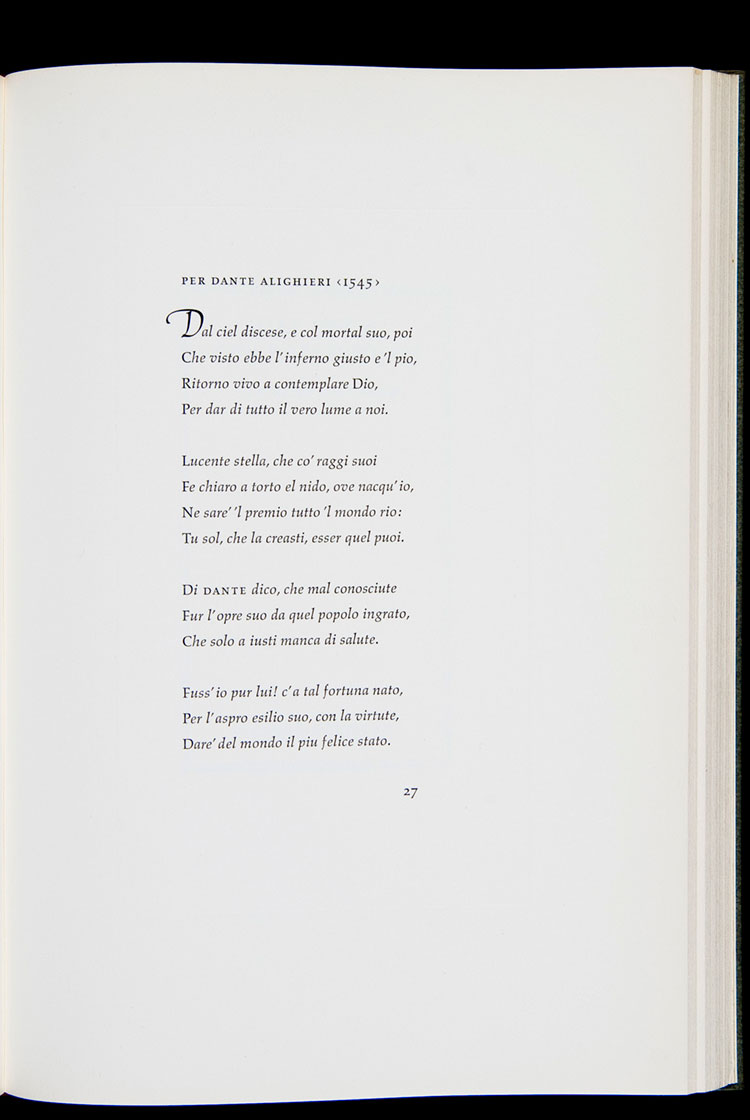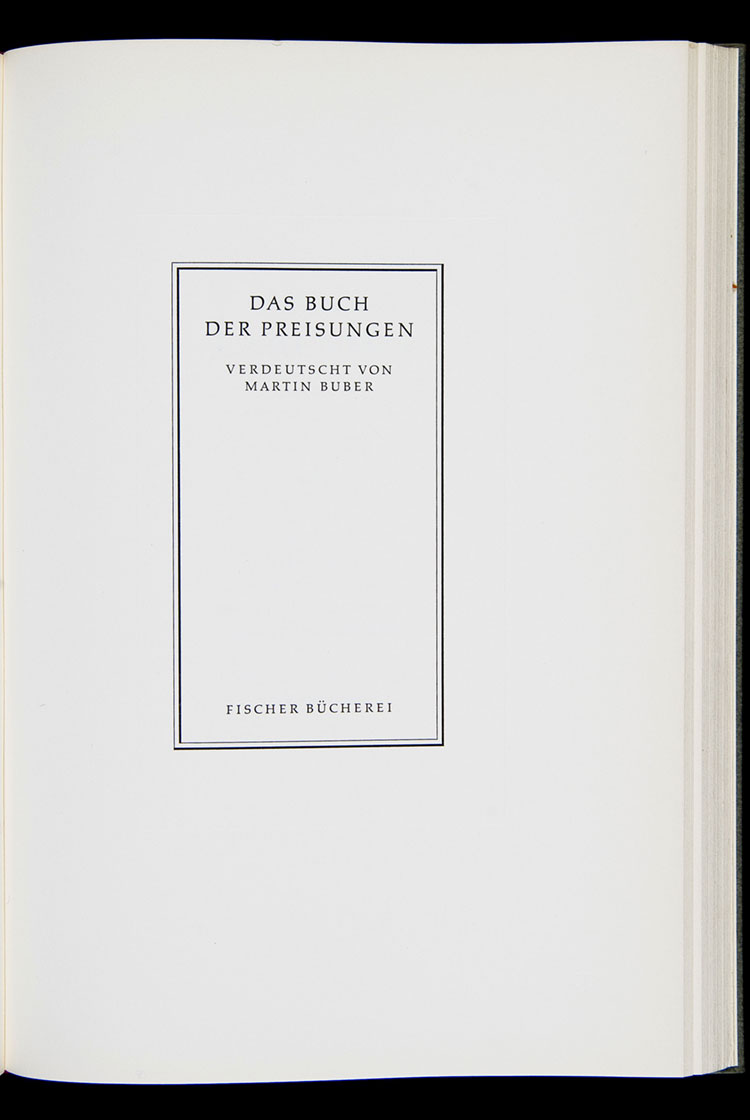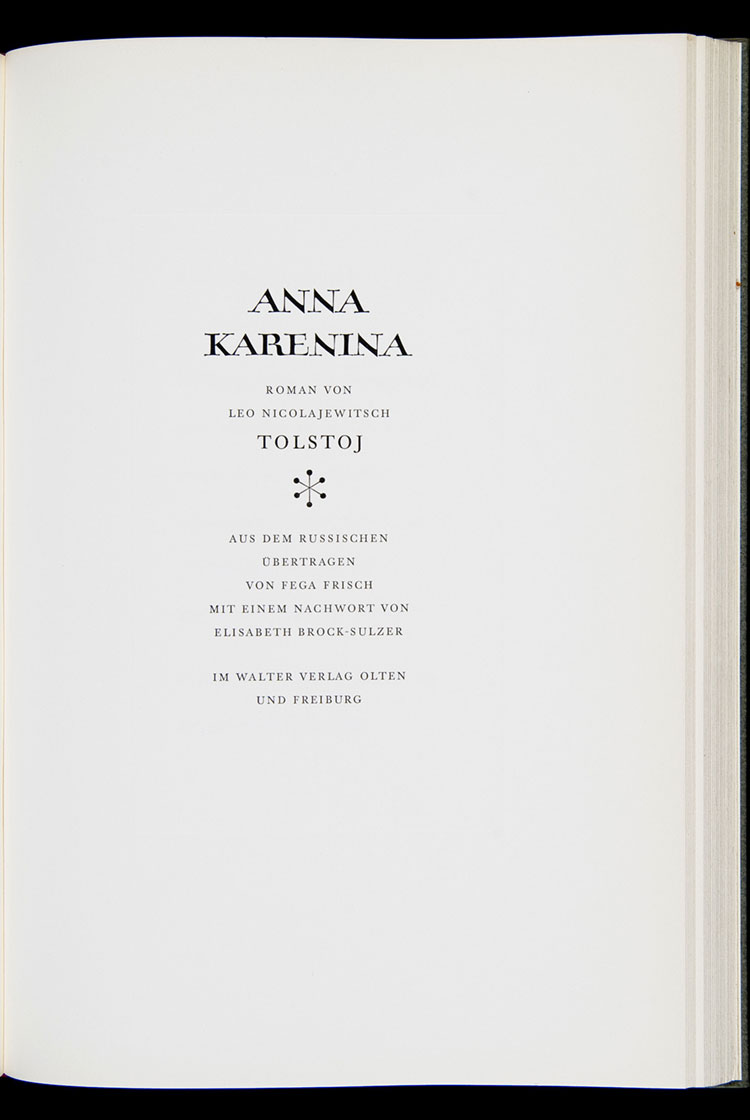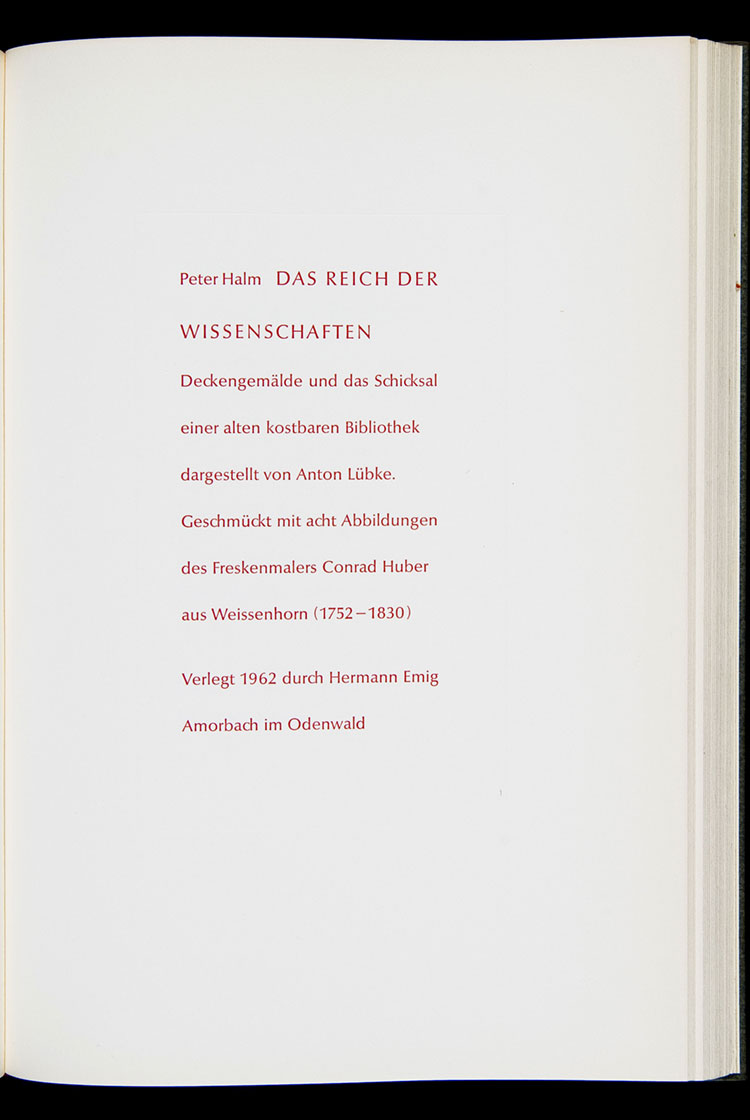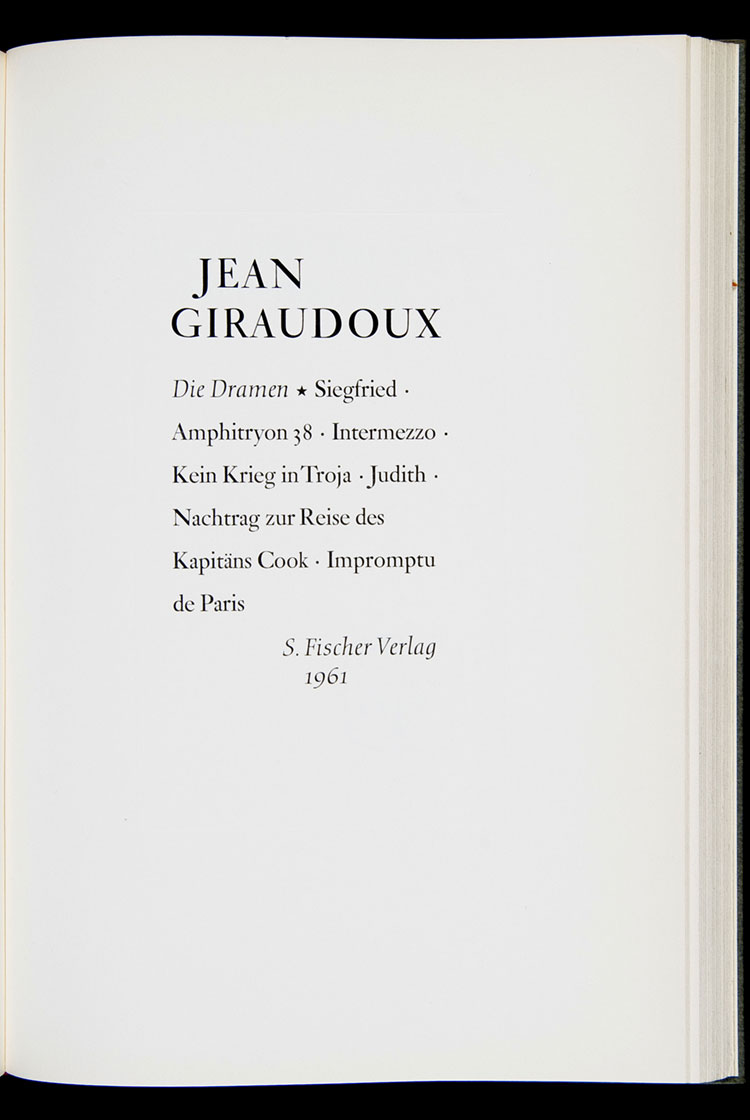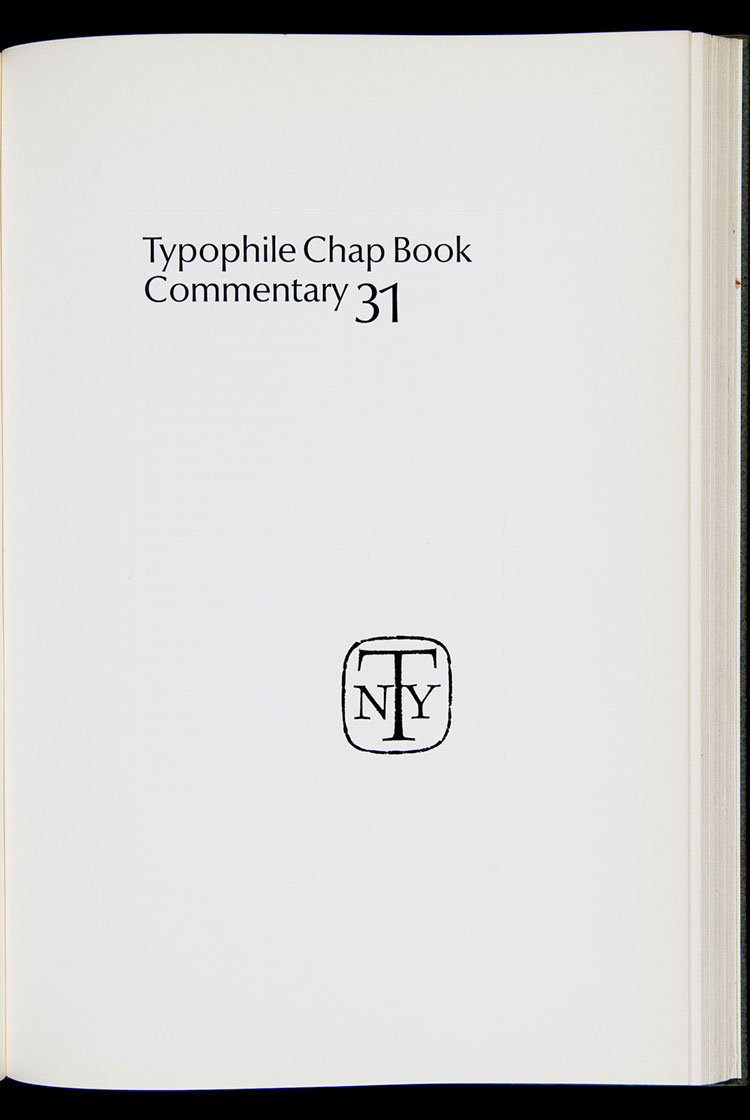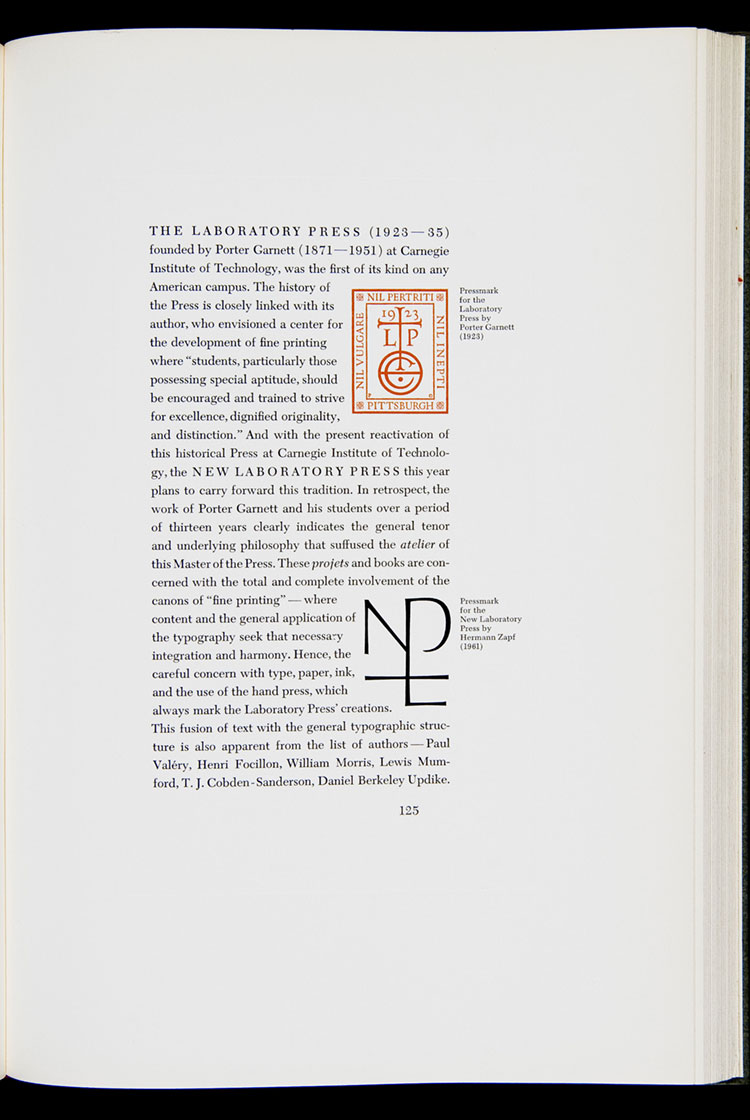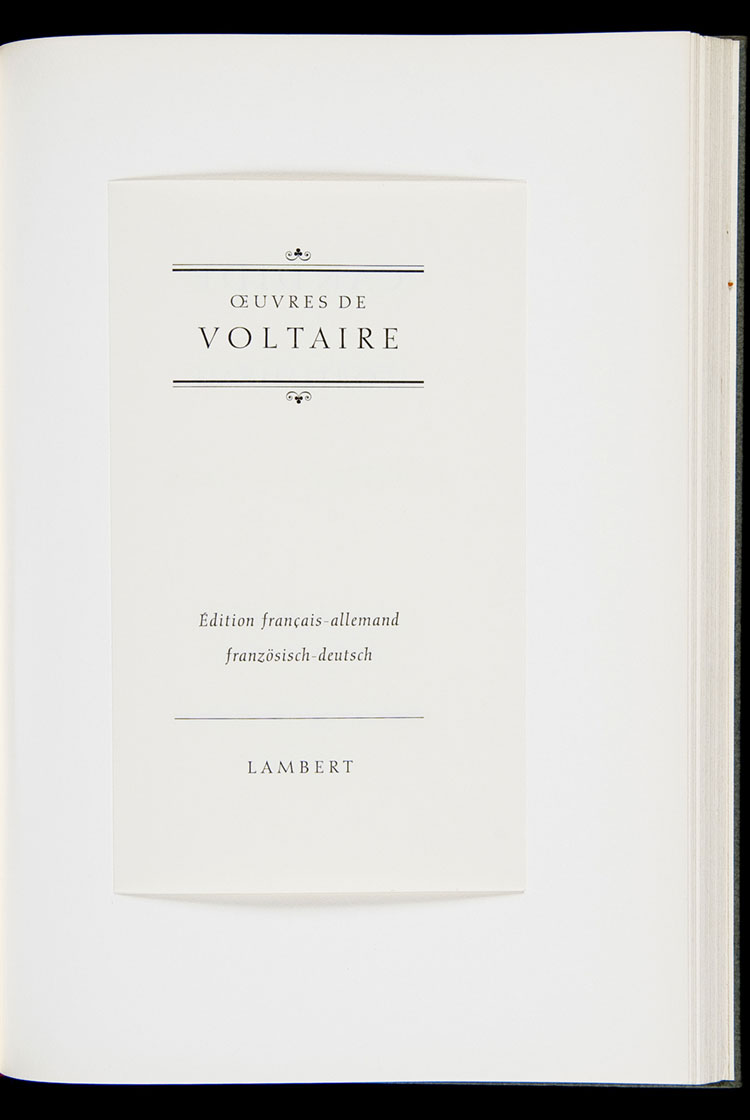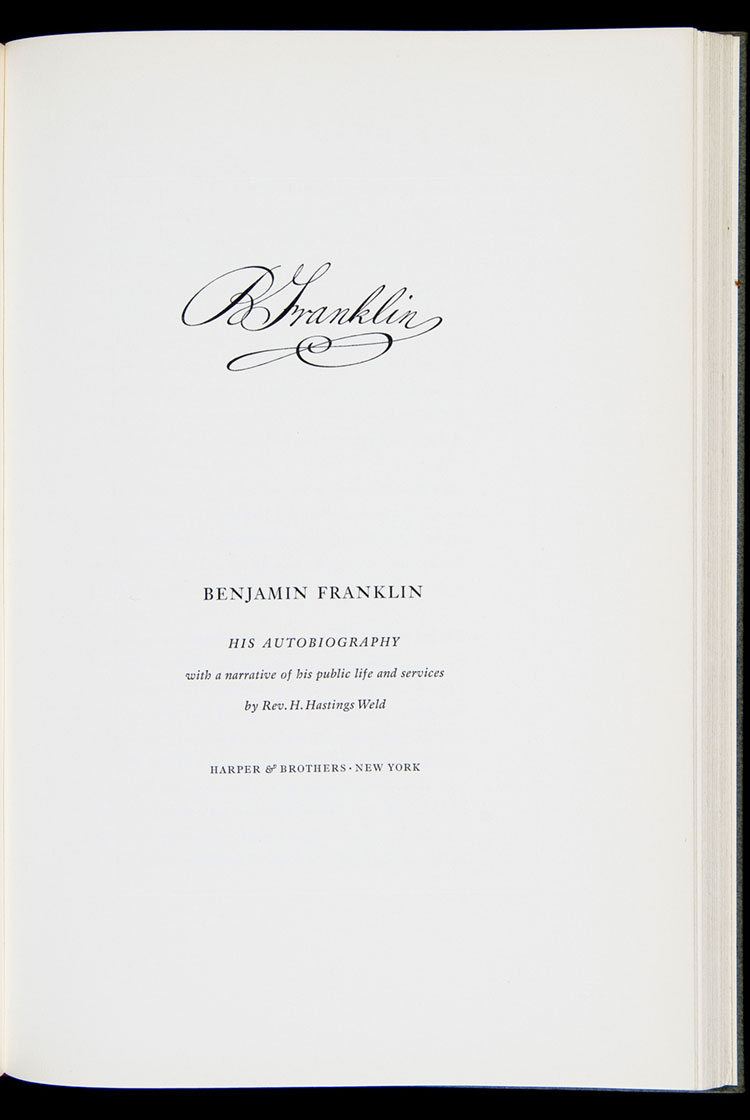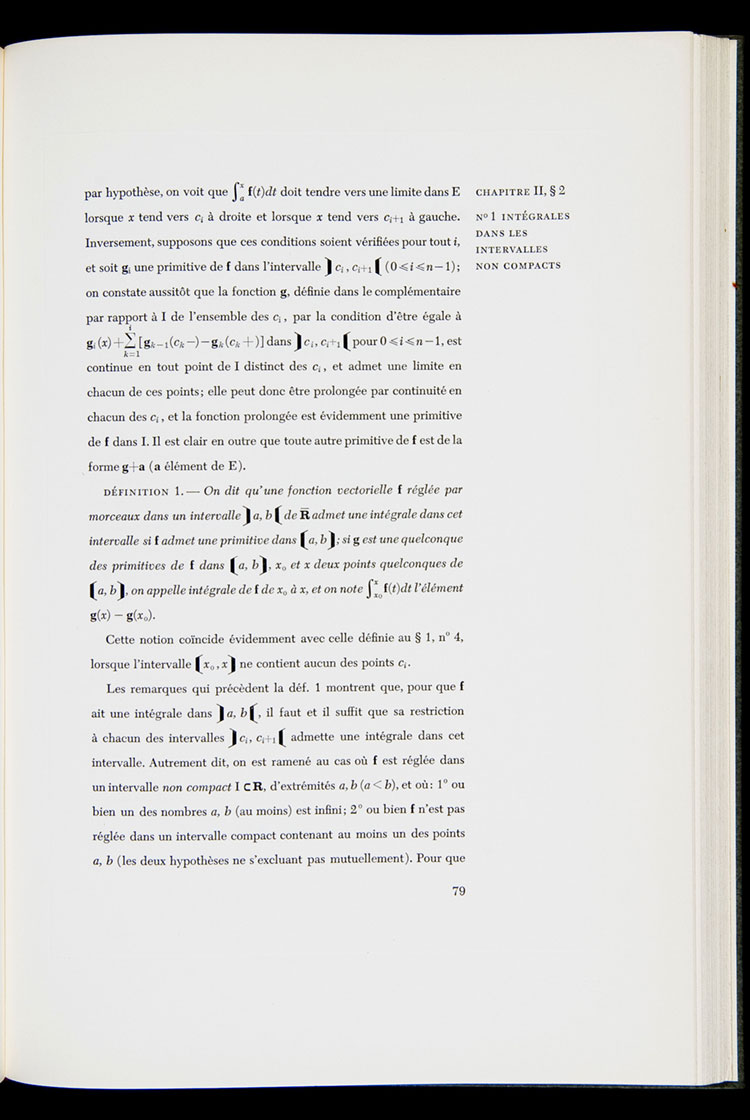
Hermann Zapf | Le deuxième Manuel Typographique au service du Livre (part.2)
Voici comme promis la suite et fin de cet ouvrage dont j’ai publié la première partie ici.
Pour ceux qui ne connaissent pas bien l’œuvre d’Hermann Zapf, je vous invite à vous reporter à une suite d’articles que j’ai écrit sur ce Maître de la Typographie contemporaine (encore vivant) ici. Et surtout d’aller découvrir le premier Manuel Typographique (Manuale Typographicum) dans les Galeries de Design et Typo ici.
Il faut bien être conscient 1) que nous sommes au milieu du XXe siècle —composition en plomb, impression typographique et non offset— 2) qu’il s’agit d’un ouvrage destiné à montrer une centaine d’exemples de mise en page consacrées à l’édition de livres et non destinées à la publicité ou à l’affiche. Car l’édition obéit à des règles bien plus classiques et moins tourmentées que l’art graphique au service des métiers de la communication voire de la culture. Et je ne parle même pas des couvertures de livres qui depuis longtemps font l’objet d’attentions particulières de la part des éditeurs et où l’innovation et les transgressions ont été nombreuses.
Pour vous rappeler l’œuvre majeure d’Hermann Zapf, voici quelques unes des polices de caractères dessinées par ce maitre de la Calligraphie et plasticien de la forme alphabétique:
Aldus (1954) Aurelia (1983) Edison (1978) Kompakt (1954) Marconi (1976) Medici Script (1971) Melior (1952) Noris Script (1976) Optima (1958) Optima nova (2002) Orion (1974) Palatino (1950) Palatino nova (2005) Palatino Sans (2007) Saphir (1953) Sistina (1950) Vario (1982) Venture (1969) Linotype Zapf Essentials (2002) Zapfino (1998) Zapfino Extra (2003) ITC Zapf Chancery (1979) ITC Zapf International (1976) ITC Zapf Book (1976) Zapf Renaissance Antiqua (1984–1987) ITC Zapf Dingbats (1978).
Qui d’entre vous n’a pas entendu parler de l’Optima ou du Palatino ou encore des Zapf Dingbats? Il n’en reste pas moins que son œuvre couvre un champ bien plus vaste. Non seulement créateur d’alphabets mais aussi théoricien et praticien des espaces typographiques, il enseigna son art pendant longtemps au MIT de Massachussets.
C’est avec un plaisir immense que je vous fais ici partager cette deuxième partie du Deuxième Manuel Typographique d’Hermann Zapf. Observez la délicatesse et l’élégance des mises en page, son sens du rythme vertical et cette douce tendresse qu’il déploie chaque fois qu’il peut pour tenter de transgresser les règles séculaires de l’édition.